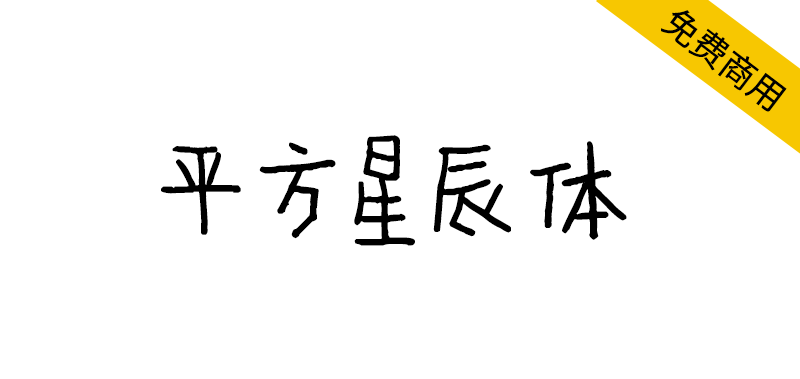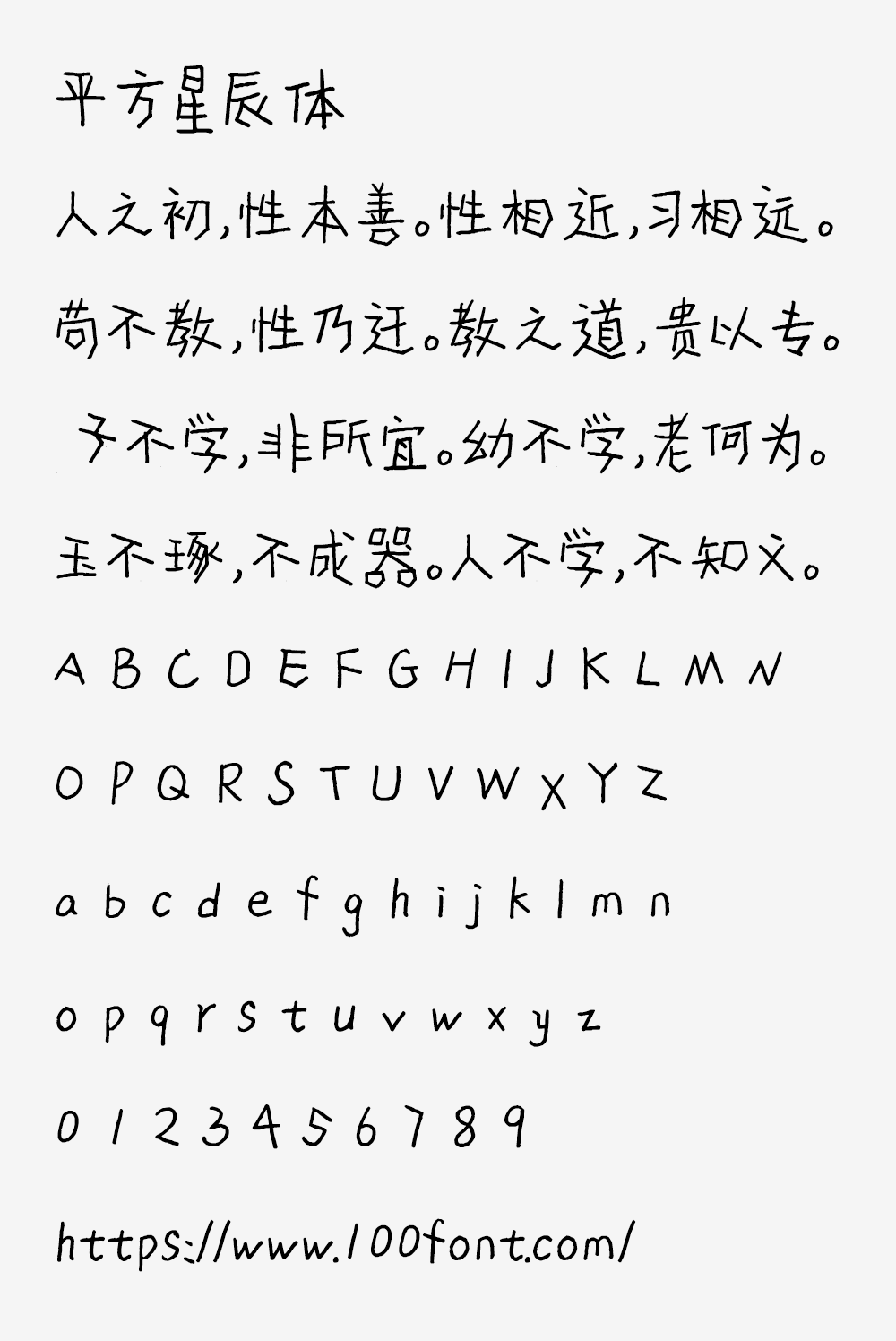
【平方星辰体】一款带有文艺风格的手写体字体
想为设计注入独特的文艺灵魂?这款「平方星辰体」或许正是你寻觅已久的答案。它用流畅均匀的线条勾勒出手写温度,更在横折钩、竖钩处藏入不规则笔触——正是这精心设计的「不完美」,让每个字都散发着迷人的艺术韵味。最惊喜的是,它完全免费商用!无论是广告、自媒体还是电商设计,都能立即赋予作品与众不同的气质。
【平方星辰体】一款带有文艺风格的手写体字体
平方星辰体是一款充满文艺气息的手写风格字体,其线条流畅均匀,在横折钩和竖钩的转折处采用独特的非规则笔触设计,使其整体效果更显文艺艺术韵味。